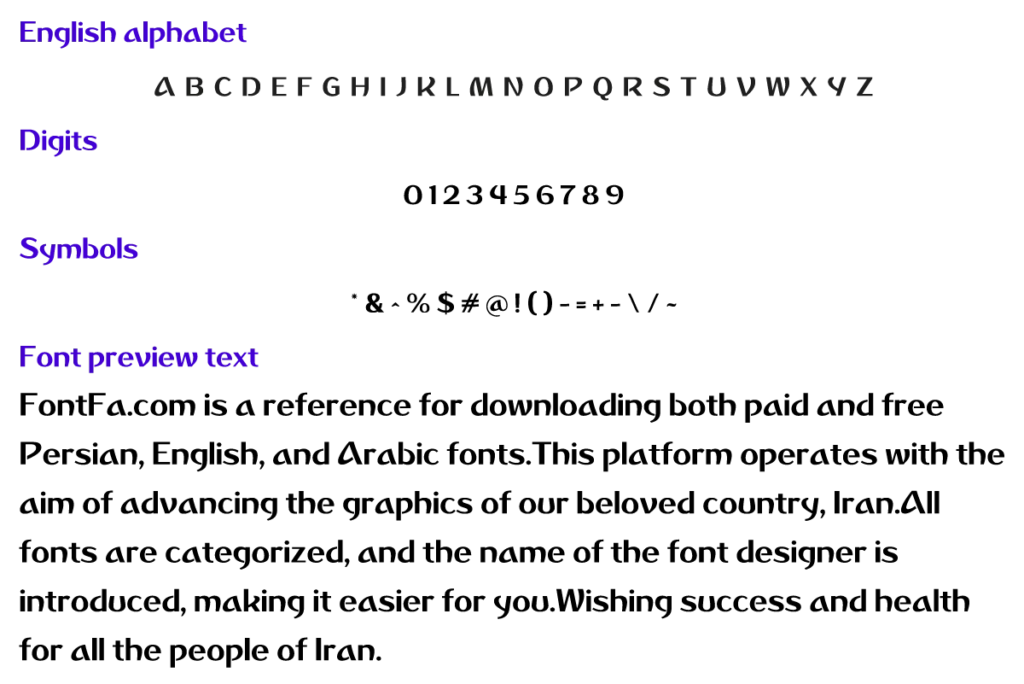
فونت انگلیسی فیفا – Dusha FIFA
توضیحات و معرفی فونت فیفا
فونت انگلیسی فیفا ( Dusha FIFA ) از مجموعه فونت های لاتین می باشد، همچنین نوع فونت تایپوگرافی می باشد.
فونت فوق العاده زیبای معرفی شده در سال 2018 برای جام جهانی فوتبال طراحی و ساخته شده است.
همچنین فونت فیفا در یک وزن پر رنگ است.